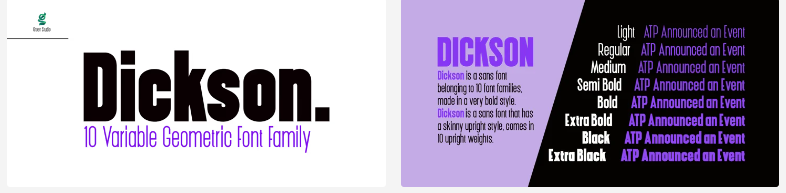
[Myfonts] Dickson Font Family (2022)
Dickson - шрифт sans, принадлежащий к 10 семействам шрифтов, выполненный в очень жирном стиле. Dickson - это шрифт sans, который имеет тощий вертикальный стиль, представленный в 10 вертикальных весах.
Dickson хорошо подходит для всех брендов, логотипов, журналов, фильмов. Различные веса дают широкое применение, а начертание шрифта придает настоящий современный вид любому проекту.
Dickson - шрифт sans, принадлежащий к 10 семействам шрифтов, выполненный в очень жирном стиле. Dickson - это шрифт sans, который имеет тощий вертикальный стиль, представленный в 10 вертикальных весах.
Dickson хорошо подходит для всех брендов, логотипов, журналов, фильмов. Различные веса дают широкое применение, а начертание шрифта придает настоящий современный вид любому проекту.